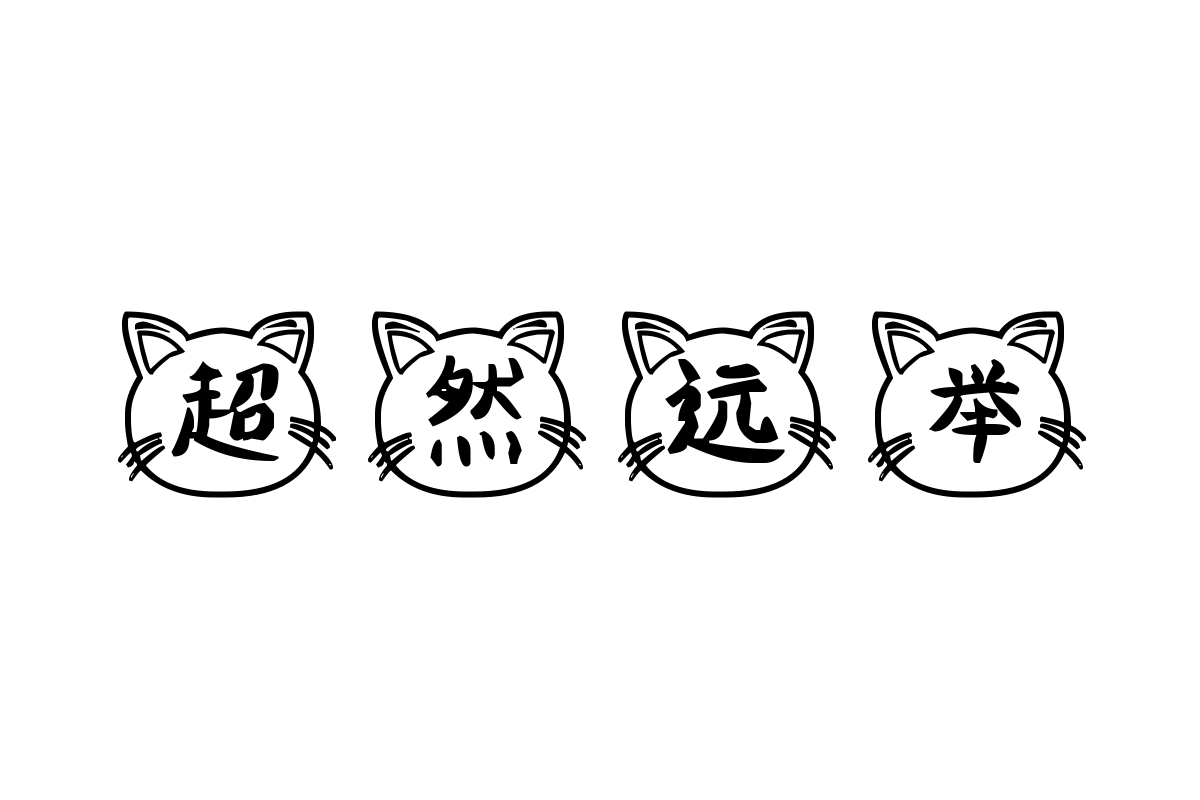
汉呈一起喵喵体是一种可爱的字体,其特点是笔画圆润、流畅,给人一种温馨、可爱的感觉。这种字体在设计中常用于儿童插画、卡通形象等场景,能够很好地传达出童趣和亲和力。
汉呈一起喵喵体的笔画粗细适中,既有粗犷的线条,又有细腻的细节,使得整体看起来既有趣又富有层次感。同时,该字体还具有很好的可读性,无论是在印刷还是电子屏幕上都能够清晰展示。
总的来说,汉呈一起喵喵体是一种非常适合用于表达童趣和可爱的字体,无论是在平面设计还是动画制作中都有很好的应用前景。